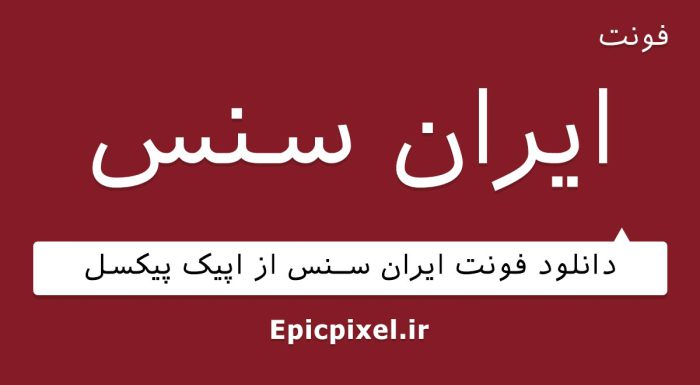
فونت ایرانسنس چیست ؟فونت هایی که سبک قدیمی یا همون Old Style دارن حس دست ساز بودن و قدیمی بودن رو به شما میدن که شاید یکی از دلیلاش همین سریف هایی که توی فونت های قدیمی خیلی به چشم میاد هست. سریف همون سرک ها هستن و توی نسخه های قدیمی می تونین خیلی خوب اونا رو پیدا کنین فونت اسما فارسیدانلودیکی از فونت هایی که از زمان عرضه اش یعنی سال 1393 تا الان تونسته با ویژگی های خفن و آپدیت های جدیدش غوغا به پاکنه فونت ایران سانس هست. این فونت با پسوند های مختلفی مثل TTF , EOT , Woff , Woff2هست. در ادامه چند مورد از ویژگی ها را توضیح میدیم براتون فونت ایران سنس با اعداد فارسی: توی این نسخه از فونت ایران سنن همه اعداد انگلیسی به شکل فارسی هم نوشته می شن. فونت ایران سنس به جز زبان فارسی، همۀ کارکترهای زبان عربی، انگلیسی و دیگر زبان های خاورمیانه ای مانند اردو و کردی را شامل می شود. اعراب گذاری این فونت نیز بسیار دقیق است. نسخه ایکس فونت ایران سنس یک تایپ فیس جدید هست که بیشتر سعی کرده پیچ و تاب حروف رو به نمایش بذاره و کمتر از خطوط شکسته و خطوط صاف استفاده کنه. میشه گفت ریشه این فونت زیبا به فونت نسخ برمی گرده ولی در پس زمینه فونت می تونین حالت ها و کش و قوس های فونت نستعلیق رو هم ببینین. 3 فونت انوش فارسیدانلودقدرتنمایی و فونت ایران سنس موبایل به همون اندازه ای هست که این فونت توی ویندوز 10 درخشیده! دانلود فونت ایران سانس برای موبایل و اندروید بسیار آسونه و شما به راحتی می تونین اون رو داخل گوشی همراه و یا حتی نرم افزار های اینشات، پیکس آرت و … خودتون نصب کنین.
تاریخچه فونت ایران سنسدر سال 1393 این فونت در یکی از شرکت های استارتاپی متولد شد و همین باعث شد که فونت ایران سنس تبدیل به یکی از المان های جامعه استارتاپی ها بشه. تنها یک سال بعد از انتشار و عرضه این فونت، بیش از 15 درصد سایت ها و اپ های موبایل از فونت hdvhk sks استفاده می کردن و این آمار تو سال های بعد به 56 درصد رسید و حتی 4 سال بعد که یه عالمه فونت جذاب و متنوع دیگه هم اضافه شده بود، بازهم فونت ایران سنس تونست با 54 درصد استفاده توی اپ های مختلف مثل کافه بازار و دیوار و دیجی کالا و… برتری خودش رو حفظ کنه.
دانلود مجموعه فونت ایران سنس به شما این امکان رو میده که بتونین خوانایی و راحتی رو به کاربرای کسب و کارتون هدیه بدین. فرقی نداره که دانلود فونت ایران سنس برای وردپرس باشه یا دانلود فونت ایران سنس برای اپ های سامسونگ یا موبایل دیتا های دیگه، فونت ایران سانس تونسته بیشترین امتیاز خوانایی رو کسب کنه. 4 فونت خاص فارسی Khassدانلودبرای درک بهتر این ویژگی فونت ایران سنس فونت های زیر رو تست کنید تا شما هم متوجه حس خوب استفاده از این فونت بشید. دانلود فونت IRANSans Light و اما سومین دلیل نزدیکی طراحی این فونت به اشکال اسلیمی و ایرانی و فرهنگ این مرز و بوم هست. طراح این فونت یعنی آقای مسلم ابراهیمی تمام تلاشش رو کرده تا با این فونت یک حالت زنده و پویا ایجاد کنه تا نمادی از کشور خوبمون یعنی ایران باشه. شما وقتی که مطالب رو با این فونت می خونین حس خودمونی و نزدیکی به نویسنده پیدا می کنین انگار که نویسنده رو سالهاست که میشناسین و می دونین که دقیقا داره چی میگه حالا بیاین فرض کنیم که فونتی که شما استفاده می کنین یک نماد از خودتون باشه یعنی نشونه ای از شخصیت شما یا شرکت شما باشه، این یعنی کاربرا و مخاطبای شما بصورت ناخودآگاه وقتی دارن لگو یا متن های شما رو با فونت خودتون می خونن تو ذهنشون حس آشنایی و دوستی پیدا می کنن و کاملا به شما اعتماد می کنن. نکته مهم دیگه ای که باعث می شه ذهن سریعتر بتونه از پس خوندن مطالبی که با ایران سنس نوشته شده بربیاد، قسمت نقطه گذاری های این فونت هست. 9 فونت شیراز فارسیدانلودتوی بروزرسانی های جدید فونت ایران سنس دو تا فونت دیگه هست که شما با دانلود فونت IRANSans Bold و دانلود فونت IRANSans Black حس یک فونت برتر رو به المان های طراحی تون اضافه می کنین.
فونت متغیر (وریبل فونت)یک تکنولوژی جدیدی توی فونت ها اومده که شما دیگه نیازی نیست برای اینکه همه وزن ها و شکل های مختلف فونت دلخواهتون رو داشته باشین مجبورباشین یه عالمه فونت دانلود کنین و هی دنبالش بگردین که این کدوم بود! بجاش کافیه یک فونت اصلی و مادر رو دانلود کنین و توی بخش فونت استایل مدلش رو انتخاب کنین تا حالت های مختلف فونتتون رو سریع ببینین
طراح فونت : مسلم ابراهیمی فونت آراز فارسیدانلود